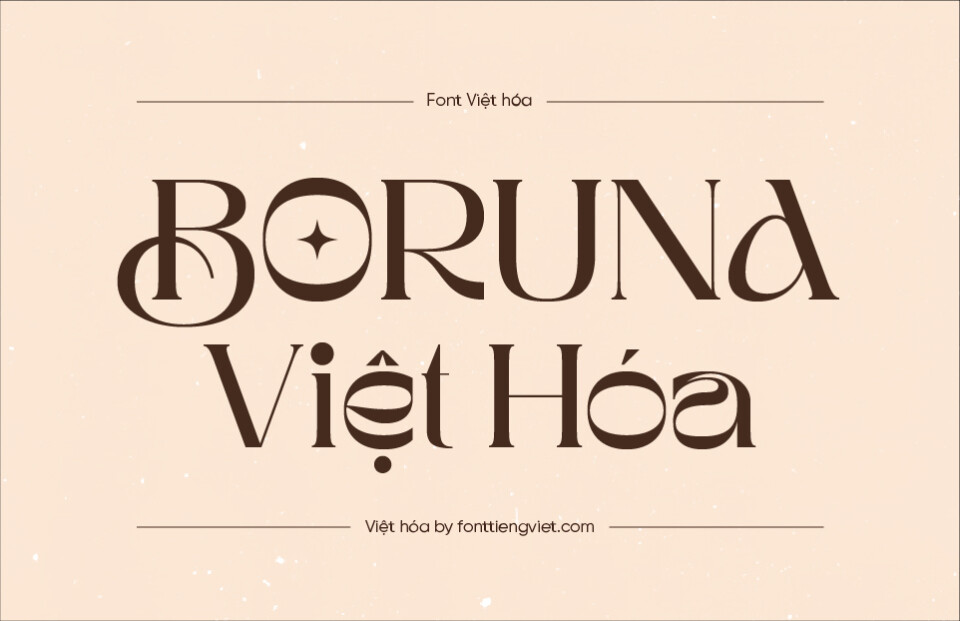
Font Việt hóa 1FTV VIP Boruna
Giới thiệu bộ Font Việt hóa 1FTV VIP Boruna
Trong thế giới đồ họa hiện đại, việc sở hữu một bộ Font Việt hóa 1FTV VIP Boruna chất lượng là điều vô cùng cần thiết đối với các nhà thiết kế và học sinh sinh viên. Đây là một phông chữ mang phong cách hiện đại, thanh lịch nhưng không kém phần mạnh mẽ, giúp các tác phẩm sáng tạo trở nên chuyên nghiệp hơn bao giờ xếp. Khi bạn sử dụng Font Miễn Phí để làm bài tập lớn hay thiết kế slide thuyết trình tại trường học, sự tinh tế của các đường nét sẽ giúp nội dung truyền tải mạch lạc và thu hút người xem ngay từ cái nhìn đầu tiên.
Đặc điểm nổi bật của phông chữ Boruna
Bộ phông chữ này được tối ưu hóa hoàn toàn cho bảng mã tiếng Việt, đảm bảo không xảy ra lỗi hiển thị các ký tự có dấu phức tạp. Font Việt hóa 1FTV VIP Boruna sở hữu cấu trúc chữ cái cân đối, khoảng cách kerning được tinh chỉnh kỹ lưỡng giúp văn bản dễ đọc trên cả thiết bị di động và bản in. Điều này cực kỳ quan trọng trong môi trường giáo dục, nơi yêu cầu sự rõ ràng và chuẩn mực trong trình bày văn bản.
Cách ứng dụng Font Việt hóa 1FTV VIP Boruna hiệu quả
Để tận dụng tối đa vẻ đẹp của bộ font này, bạn có thể áp dụng vào nhiều mục đích khác nhau:
• Thiết kế tiêu đề báo tường, thiệp mời sự kiện nhà trường.
• Làm nội dung chính cho các bộ nhận diện thương hiệu cá nhân.
• Trình bày đồ án môn học cần sự sang trọng và khác biệt.
Việc lựa chọn Font Việt hóa 1FTV VIP Boruna không chỉ giúp tiết kiệm thời gian chỉnh sửa mà còn khẳng định gu thẩm mỹ tinh tế của người sử dụng.
Kết luận về bộ font chữ VIP